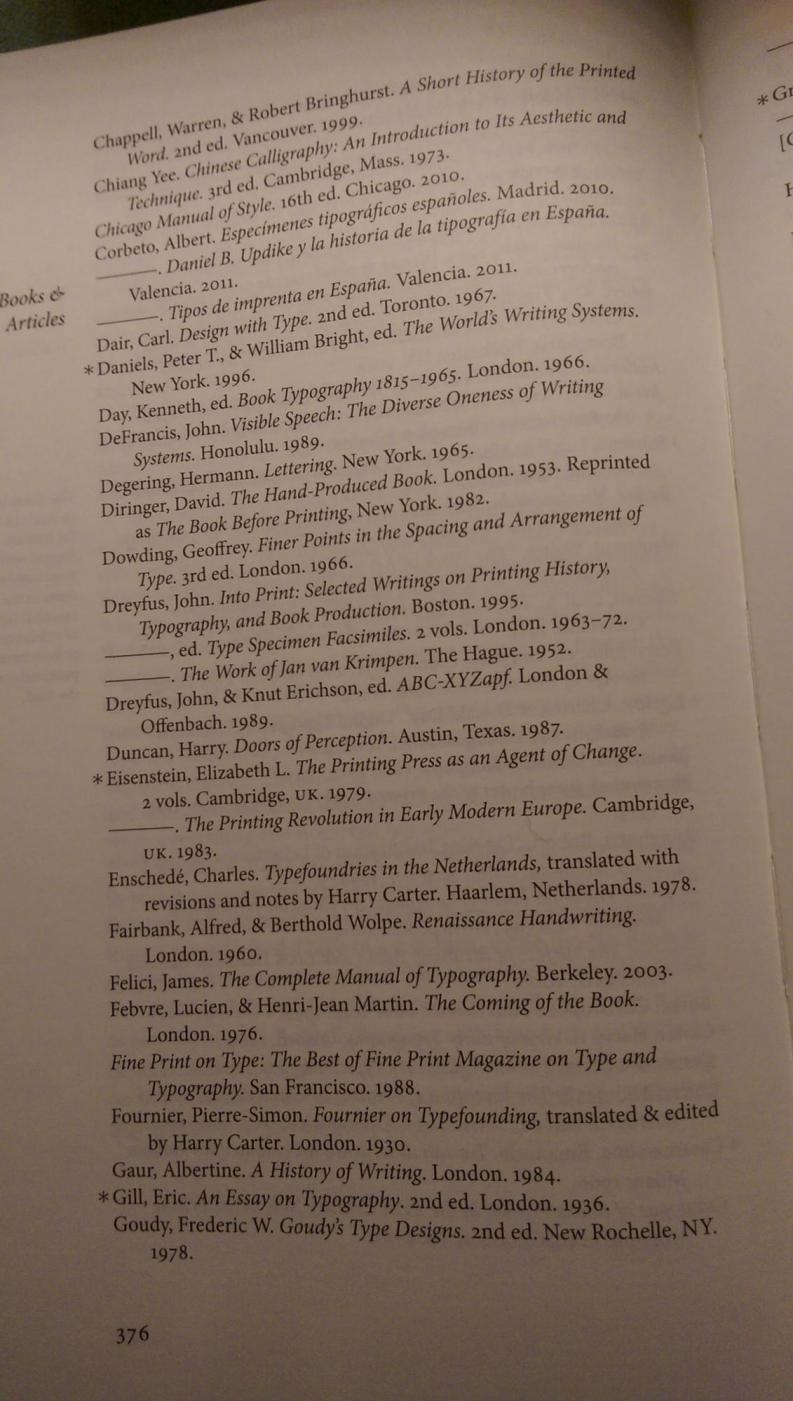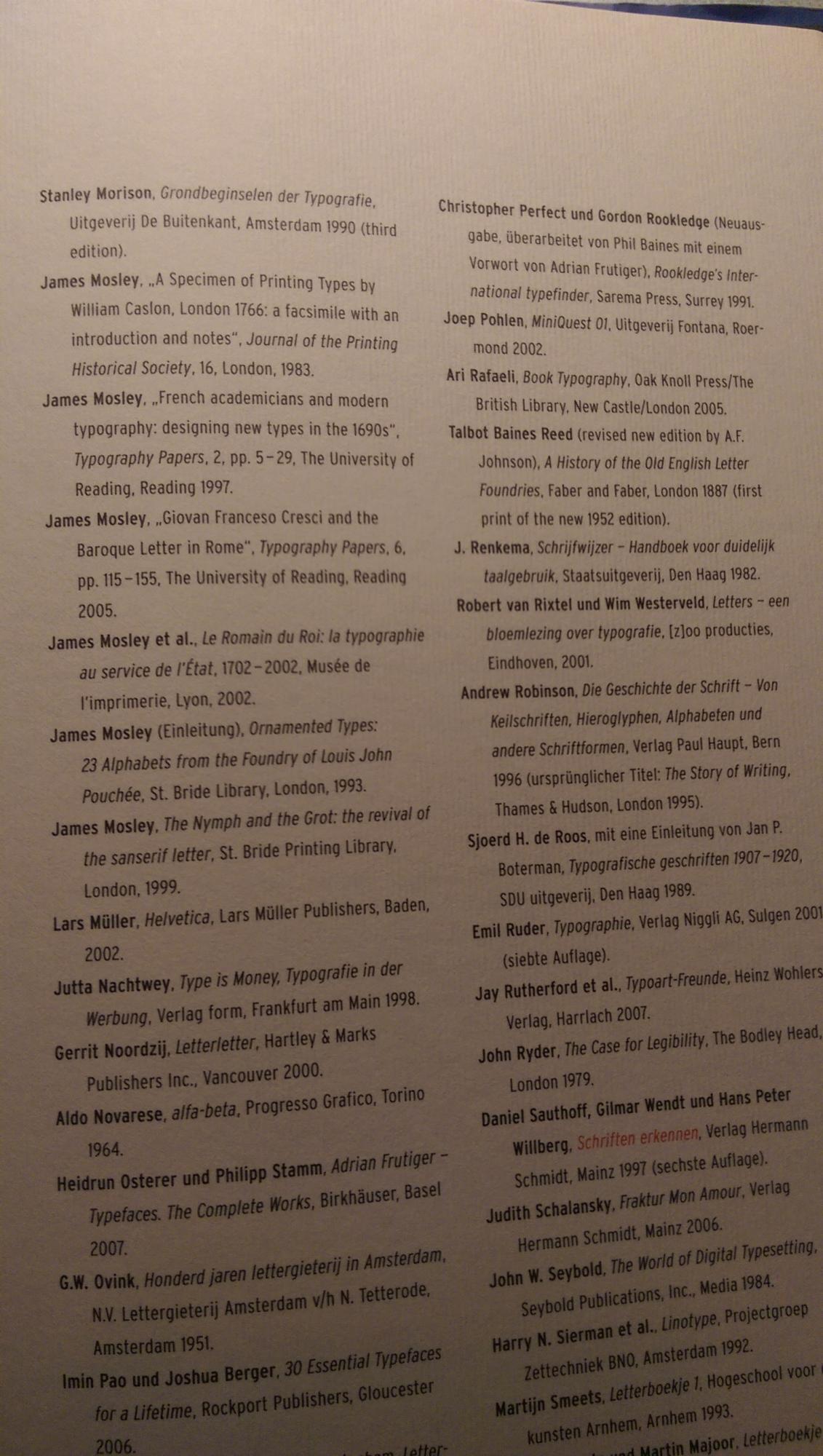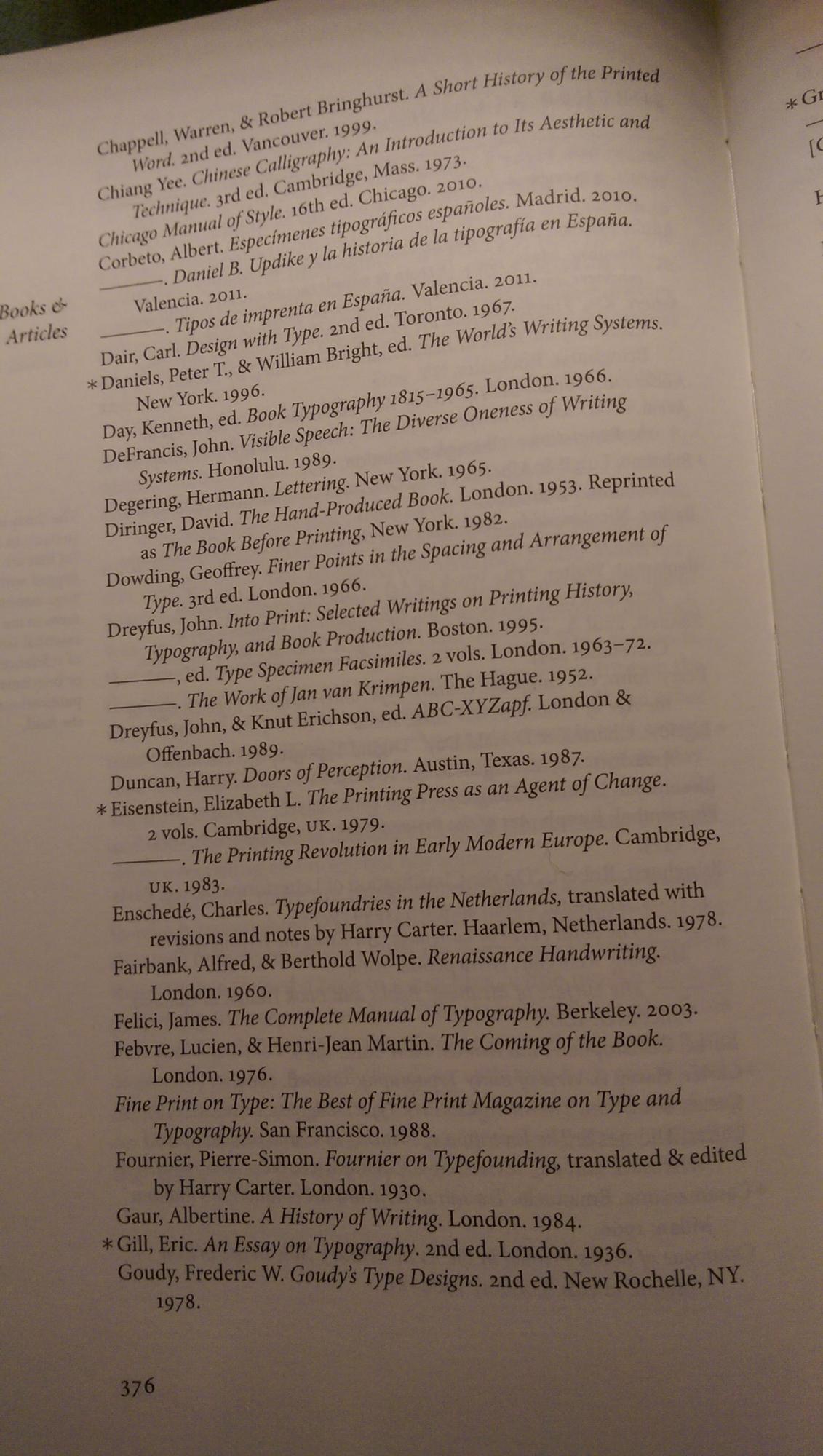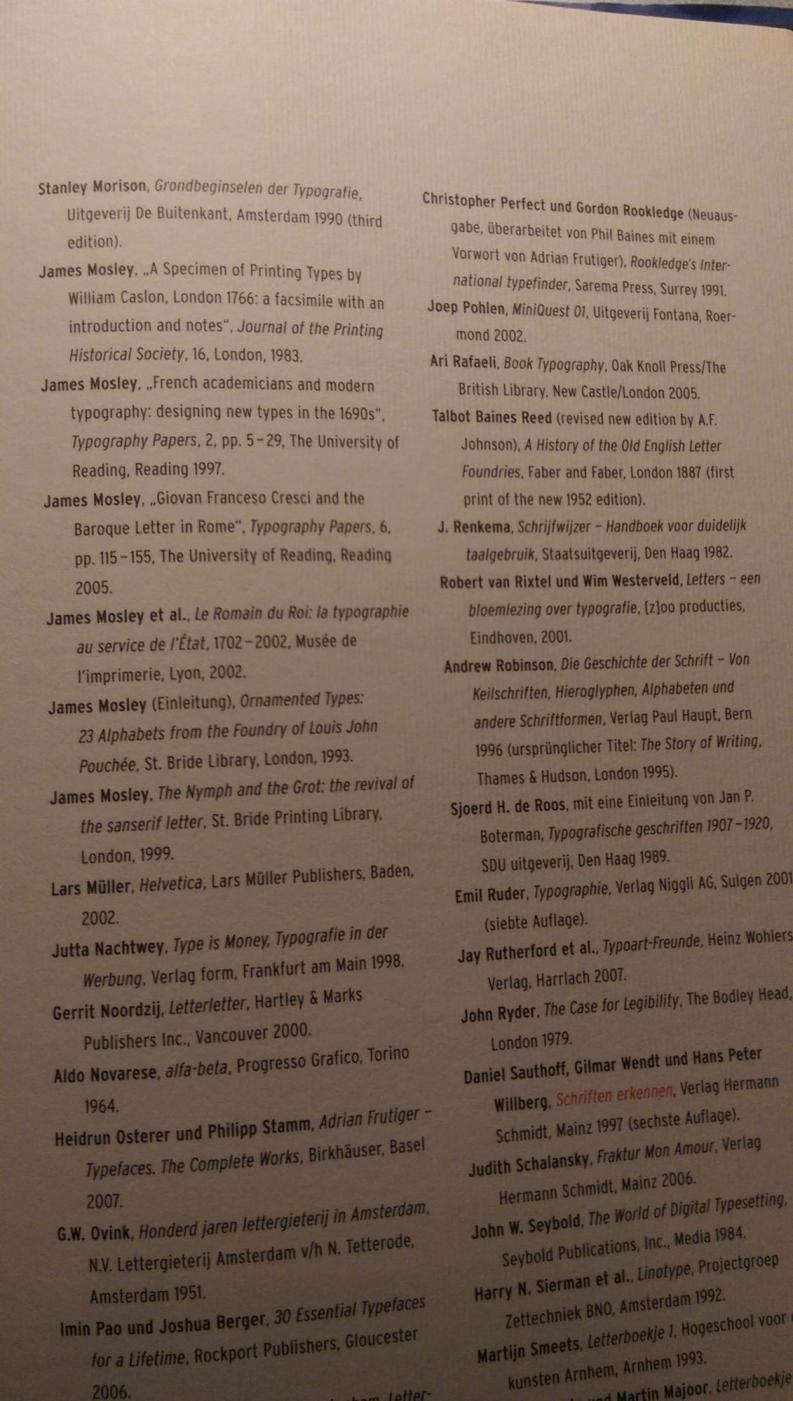
Dass wir angesichts der Gleichwertigkeit der Alternativen nicht wie Buridans Esel zwischen zwei gleichartigen Heuhaufen verhungern, hat nicht zuletzt auch etwas mit bestimmten Lesegewohnheiten zu tun.
Und ich gebe Dir darin ausdrücklich recht, dass bei einem nennenswerten Anteil von Titeln, die in eine Zeile passen, das Einrückungssystem partiell leerläuft und funktional unterlegen ist. Da in meinem Fachgebiet aber mehrzeilige Titel (u.a. wegen des hohen Anteils von Zeitschriftenartikeln) stark überwiegen, ziehe ich die Einrückungsvariante vor, ohne der von Dir favorisierten Durchschussvariante ihre Berechtigung zu bestreiten.
Lieber @R::bert, die Schriftmischung war hier nur ein Nebenschauplatz. Doch weil mich Dein scharfes Auge und Dein subtiles Urteil beeindruckt und überzeugt haben, habe ich die Schrift des Kommentars geändert.
Mich würde - unabhängig von allen anderen Fragen, die jemand von Deiner Kompetenz zu einer Vorlage von Laienhand wie der meinen jederzeit aufwerfen könnte - interessieren, wie Du Dich zu der von @Microboy aufgeworfenen Frage positionieren würdest, nämlich ob ein Literaturverzeichnis als Konsultationstext besser mit Mediaeval- oder mit Versalziffern funktioniert (er meinte Letzteres).
Und da ich die fachmännische Antwort ahne, "das hängt (u.a.) von der verwendeten Schrift ab", füge ich hinzu: Wenn des Literaturverzeichnis in der Muriza oder einer ihr ähnlichen Slab gesetzt ist.
Die Gliederung eines Literaturverzeichnisses ohne hängende Einrückungen durch größeren Durchschuss zu bewerkstelligen, habe ich oben bereits als eine gleichwertige Alternative anerkannt. Weshalb sie eine objektiv überlegene Variante sein soll, erschließt sich mir nach wie vor nicht.
Wäre ja interessant, wenn man es mal ausprobieren und vergleichen könnte :-?Dann könnte man sagen, ob es theoretisch eine gleichwertige Variante ist, oder ob es vielleicht besser funktioniert.
Wer mit Literaturverzeichnissen weder privat noch beruflich etwas am Hut hat, den wollte ich mit meinen Fragen nicht behelligen oder zu Stellungnahmen nötigen.
Dann theoretisiere hier mal weiter vor dir hin, ich will dich auch gar nicht groß nerven. Aber als Designer beschäftigt man sich zwangsläufig mit Dingen zu den man persönlich kaum direkten Bezug hat. Dass ich nicht regelmäßig Literaturverzeichnisse durchackere, heißt nicht, dass ich mich nicht mit deren Gestaltung auseinandersetzen will/kann. Ich kann lediglich nicht die Lesegewohnheit abrufen.
Wäre ja interessant, wenn man es mal ausprobieren und vergleichen könnte :-?Dann könnte man sagen, ob es theoretisch eine gleichwertige Variante ist, oder ob es vielleicht besser funktioniert.
Bitte sehr ... hier sind beide Varianten auf zwei getrennten Seiten. (Die namensersetzenden Striche tun ohne Einrückungen weniger gute Dienste; daher habe ich sie ersetzt.)
Passabel sieht m.E. beides aus - am Ende entscheidet wohl, wie gesagt, die Lesegewohnheit. (Ich zähle eher zu den platzsparenden Einrückern als zu den großzügigen Durchschießern.)
Mich stören ja bei den Versalziffern sofort die Kollisionen zwischen den Klammern und der ersten/letzten Zahl. Da müßte man mehr Luft geben um das zu entschärfen. Bei den Seitenangaben sitzt dann der Gevierstrich zu tief, weshalb ja die wirklich guten Schriften auch unterschiedliche Versionen haben. Kommt dann natürlich drauf an was einen persönlich mehr stört, aber mit Versalfziffern sieht es für mich einfach zu sehr nach selbst-gestrickter Diplom- oder Doktorarbeit aus, von denen ich viel zu viele in die Hände bekomme. Ich persönlich würde ohne Mehraufwand die Version mit Mediävalziffern deutlich bevorzugen. Aber das ist nur meine persönliche und unprofessionelle Meinung. :tuschel::-|
Ja, auch wenn es vielleicht keine buchstäblichen Kollisionen sind, so ist doch der geringe Abstand zwischen Klammern und Zahlen tatsächlich weder schön noch lesefreundlich - die Anmutung hat einen klaustrophobischen touch. Das ist vielleicht bei anderen Schriften anders und minder auffällig, aber es ist tendenziell ein problematischer Punkt. Hier händisch einzugreifen, wäre ein großer Aufwand, den Mediaevalziffern mit hoher Wahrscheinlichkeit nicht erfordern.
Ja, die Harrison ist etwas speziell. Ich denke, ihre Stärken hat sie in kleineren und größeren Graden, sozusagen als Caption (vielleicht auch für Marginalien zu einer passenden Sans) einerseits und als Subhead-/Displayschrift andererseits. In normaler Lesegröße würde ich sie nur für kurze Texte verwenden; für den Zauberberg ist sie sicher weniger geeignet ... :-)